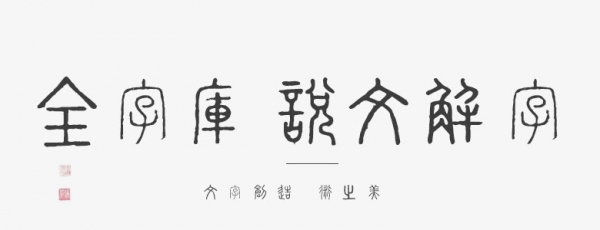
全字庫說文解字是一款很特別的小篆風(fēng)格中文字體,具有一種古色古香的歷史韻味,以《中國 臺 灣 政 府資料開放授權(quán)條款-第1版》的授權(quán)許可的方式發(fā)布。
《說文解字》是中國第一部系統(tǒng)地分析漢字字形和考究字源的字書,許慎著,成于安帝建光元年(121年)。原書十四篇,敘目一篇,正文以小篆為主,收9353字,又古文等異體同文1163字,解釋十三萬余字。
目前采用的版本為藝文印書館所出版之《說文解字注》,后由南唐徐鉉所校定,清代段王裁注之版本(世稱大徐本)并參考黎明文化事業(yè)公司之《說文解字注》,及南唐徐鉉所撰之《說文解字繁傳》
由于說文解字原文與現(xiàn)行之Unicode編碼并無一完整的對應(yīng),因此無法將所有的字形收錄于本字體內(nèi),所以會有部分字碼無法顯示出正確的字形,使用的時候請多留意,目前收錄于本字體內(nèi)的字?jǐn)?shù)共6721個字。